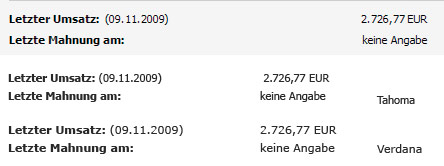
Sicher eine Windows-Standardschrift – aber welche?
Schau Dir mal die Ziffern, das »M« und das Komma an. Das ist sicher doch entweder Tahoma oder Verdana, auch wenn es auf den ersten Blick nicht so ausschaut in Deinem Screenshot. Sonst sag doch mal, warum Du meinst, dass es nicht eine von den beiden sein kann.
hm, ich komm im Photoshop so gar nicht in die Nähe der Vorlage … was mach ich denn da falsch? Oben jeweils Tahoma in den 5 Stufen …
doch, tahoma mit antialiasing sollte es sein. :gimmifive:
Das ist eine Systemschrift (nur) für den Bildschirm, eine Bitmapschrift, aber sicher keine Truetypeschrift. Diese Schriften haben IIRC die Extension .FNT oder .FON. Setz Dich ein einen Windows-Rechner und schaue in den Schriftenordner. Dort findest Du diese Schriften. Da musst Du einfach mal durch!
Wikipedia gibt da leider nur sehr unzureichend und dazu noch eine falsche Auskunft im letzten (!) Absatz: http://de.wikipedia.org/wiki/Bitmap-Schrift Real sind diese Schriften bei jeder GUI dabei: Windows, PM (Presentation Manager von OS/2 bzw ECS) und X11 haben da immer ein Bündel davon.
Schau mal ob Du bei den FNT oder FON eine Tahoma-ähnliche findest. Da könnten TAHOMA.FON und TAHOMABD.FON auf Dem System rumgammeln.
Ein "gängiges" Problem ... mit den Photoshop-AA-Methoden kriegt man nicht immer genau das hin, was das jeweilige System mit Hinting, Cleartype etc. zum Vorschein bringt.
Da Photoshop nicht die Systemmittel zur Schriftdarstellung verwendet, sondern seine eigenen, lässt sich das auch nicht wirklich lösen, außer man macht das Detail-Templating gleich direkt in HTML/CSS, statt in Grafikprogrammen.
ich muss da leider in ein paar Screenshots die Jahreszahlen und ein paar andere Dinge aktualisieren, da bleibt mir nur der Photoshop :D
Da Photoshop nicht die Systemmittel zur Schriftdarstellung verwendet, sondern seine eigenen, lässt sich das auch nicht wirklich lösen, außer man macht das Detail-Templating gleich direkt in HTML/CSS, statt in Grafikprogrammen.
Vielleicht kommt man ja mit GIMP for Windows näher an das Windows-Systemverhalten?
hm, ich komm im Photoshop so gar nicht in die Nähe der Vorlage … was mach ich denn da falsch? Oben jeweils Tahoma in den 5 Stufen …
Musst Du nur wenige schon vorhandene Lettern austauschen? Dann wird es einfach: Ausscheiden und rüberkleben. Ansonsten komplett den Text nachbauen, dann merkt es auch Keiner mangels Vergleichsmöglichkeit. Identischer Nachbau müsste über die (Bitmap-) Schriften und den Rendering-Algorhitmus der Oberfläche gehen.